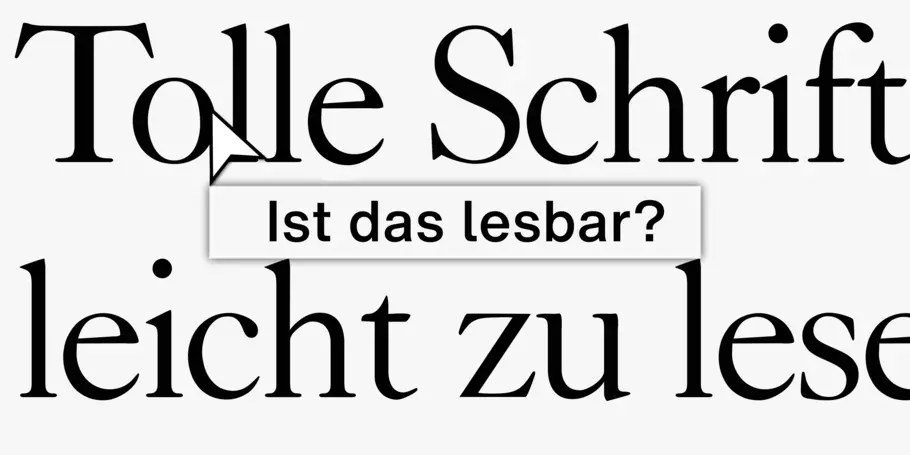
Sind die Texte auf Ihrer Website barrierefrei?
„ Die Wahl der richtigen Schrift ist wichtiger denn je, um alle Menschen zu erreichen. “
Seit 2002 gilt in Deutschland das Behindertengleichstellungsgesetz (BGG), in Österreich seit 2006 das BGStG. Die wichtigsten Ziele dieser Gesetze sind das Diskriminierungsverbot und die Barrierefreiheit – wobei Barrierefreiheit mehr ist als die Rampe vor dem Eingang oder das Blindenleitsystem im Gebäude. Barrierefreiheit spielt in allen Lebensbereichen eine Rolle, gerade auch in der digitalen Kommunikation.
Die Digitalisierung hat alle Bereiche des privaten und öffentlichen Lebens erfasst. Das Netz bietet Informations- und Austauschplattformen, hat eine große Reichweite und ist ein schier unerschöpflicher Wissensspeicher, auf den unabhängig von Zeit und Ort zugegriffen werden kann. Damit eröffnet es insbesondere Menschen mit Behinderungen neue Möglichkeiten, bringt aber auch zahlreiche Herausforderungen für die Website-Betreiber mit sich.
Neue DIN-Norm
Webentwickler, die für Behörden, öffentliche Einrichtungen und Unternehmen mit hohem Inklusionsanspruch arbeiten, werden oft gefragt, ob es Richtlinien oder Normen für barrierefreies Design gibt. Noch ist das nicht der Fall. Aber es ist bereits beschlossene Sache und nur noch eine Frage der Zeit. Der Normenausschuss Ergonomie (NAErg) beim Deutschen Institut für Normung in Berlin arbeitet derweil an einer 60-seitigen Richtlinie mit dem Namen „Empfehlungen für Deutsche Leichte Sprache“ (DIN SPEC 33429). Am 3. März 2023 wurde der Entwurf veröffentlicht (hier kostenlos zu laden), bis zum 3. Mai 2023 konnte er kommentiert werden. Die endgültige Veröffentlichung ist für Ende des Jahres 2023 geplant.
Das sechste der insgesamt neun Kapitel dieser DIN 33429 ist ganz der barrierefreien visuellen Gestaltung gewidmet. Es werden Empfehlungen zur richtigen Schrift und zur typografischen Gestaltung gegeben, wobei – ganz klassisch und praktisch – zwischen Lesetext, Beratungstext und Anzeigetext unterschieden wird. Weitere typografische Themen sind „Visuelle Gliederung und Auszeichnung“, „Grafische Elemente“ (Pfeile, Listen, Linien …), „Tonwerte und Farbe“ sowie „Verhältnis von Bild und Sprache“.
Die visuelle Gestaltung trägt auf mehreren Ebenen zur Verständlichkeit von Texten bei. Daher sollten bei der Gestaltung von barrierefreien Websites und Druckerzeugnissen die folgenden Aspekte berücksichtigt werden:
• Leserlichkeit. Sie hängt nicht nur von der sprachlichen Ausdruckweise ab, sondern auch von der visuellen Umsetzung. Ein Text wird z. B. dann leserlich, wenn der Kontrast zwischen Schrift und Hintergrund hoch genug ist oder die Schriftgröße im Bereich der Lesegewohnheiten liegt, d. h. nicht zu klein und nicht zu groß gewählt ist.
• Lesbarkeit. Dieser Begriff bezeichnet die gestalterische Qualität einer Schrift bzw. der typografischen Gestaltung. Eine Schrift ist z. B. dann gut lesbar, wenn der Strichstärkenkontrast gering ist, die Zwischenräume groß und die Buchstabenformen offen sind, und wenn die Ähnlichkeiten zwischen den verschiedenen Buchstaben gering ist (Testwort: Illiaorn).
• Strukturierung. Die Strukturierung der Inhalte erleichtert die Orientierung, erhöht die Lesbarkeit und unterstützt das Textverständnis.
• Motivation. Die Gestaltung muss den Lesenden Lust aufs Lesen machen. Ein Text in Leichter Sprache wird z. B. dann gerne gelesen, wenn die typografische Gestaltung die Textstruktur (= inhaltliche Logik) unterstützt und motivierende Gestaltungselemente enthält. Das können Initialen, Pfeile, Aufzählungspunkte, Linien und natürlich Farben sein. Aber Achtung: Nicht dekorieren, sondern strukturieren!
Auch Bilder regen zum Lesen an. Damit Abbildungen in barrierefreien Texten gut verstanden werden, sollten sie sich auf die Lebenswirklichkeit der Zielgruppe beziehen. Dazu gehört, den kulturellen Hintergrund und die Altersstruktur der Zielgruppe zu berücksichtigen. Es ist wichtig, die gesellschaftliche Vielfalt sowohl auf der Sprach- als auch auf der Bildebene widerzuspiegeln. Text und Bild sollten so miteinander kombiniert werden, dass sie direkt aufeinander Bezug nehmen und einander ergänzen. Was inhaltlich zusammengehört, sollte nah beieinander stehen.
Drei Themen verdienen in diesem Beitrag besondere Aufmerksamkeit, weil sie die Barrierefreiheit im digitalen Design dramatisch verbessern, aber auch zerstören können: Farbe, Kontrast und Live-Text.
Wie Sie Ihre Website durch Farbe barrierefreier gestalten können
Designer verwenden Farbe oft, um eine Hierarchie und Differenzierung auf einer Website zu schaffen. Dies kann jedoch die Lesbarkeit für Menschen mit Sehbehinderungen, insbesondere Farbenblindheit, beeinträchtigen. Die neue DIN 33429 für barrierefreie Texte empfiehlt daher, dass „farbige Markierungen sparsam eingesetzt werden sollten. Sie eignen sich gut als Ergänzung zu anderen Auszeichnungen. Auf ein Aufeinandertreffen von Komplementärfarben sollte verzichtet werden, da diese optisches Flimmern verursachen und dadurch die Wahrnehmung erschwert wird.“
Mit anderen Worten: Es sollte nicht Farbe allein verwendet werden, um wichtige Sätze im Text zu kennzeichnen, um Anweisungen oder Aufforderungen zum Handeln hervorzuheben oder um anzuzeigen, dass eine Aktion abgeschlossen wurde (z. B. das Anklicken einer Schaltfläche).
Dennoch ist es wichtig, über die richtigen Tools zu verfügen, wenn Sie ein Gleichgewicht zwischen Barrierefreiheit und markengerechtem Design herstellen wollen. Einer dieser Bausteine sollte eine robuste Schriftbibliothek sein, die eine Reihe von gut lesbaren Fonts in verschiedenen Stilen bietet. Zwar werden von DIN und W3C keine konkreten Schriften empfohlen; die Richtlinien können Ihnen aber dabei helfen, Fonts zu finden, die die genannten Ziele erfüllen. Mit einer gut ausgebauten Bibliothek mit soliden Optionen für Web-Fonts sind Sie auf dem besten Weg, um barrierefreie Web-Designs zu entwickeln, die Ihre Kunden zu schätzen wissen.